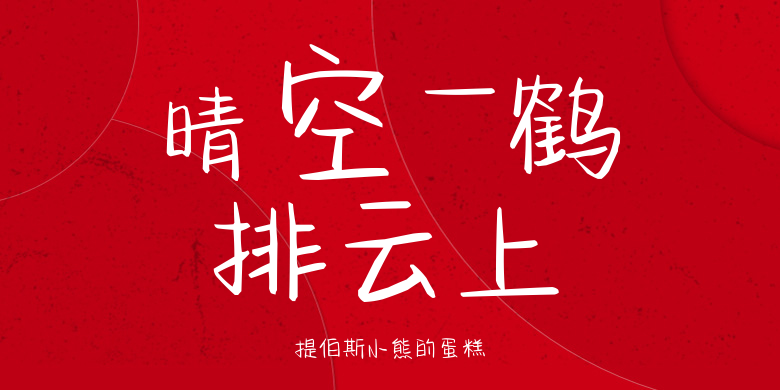
提伯斯小熊的蛋糕
提伯斯小熊的蛋糕,这款字体结构工整、笔画清晰,兼顾美观与易读性,适用于标题、正文、海报、包装、LOGO 等多种场景。字形优雅稳定,风格百搭耐看,适配日常排版与创意设计,让文字呈现更舒适、更具质感。提伯斯小熊的蛋糕一笔一画,皆是细节,以均衡的比例、流畅的线条打造舒适视觉体验,字形端正大气,风格简约现代。无论是商业设计、品牌宣传还是日常排版,都能轻松驾驭,让文字更有格调与力量。提伯斯小熊的蛋糕字体下载。